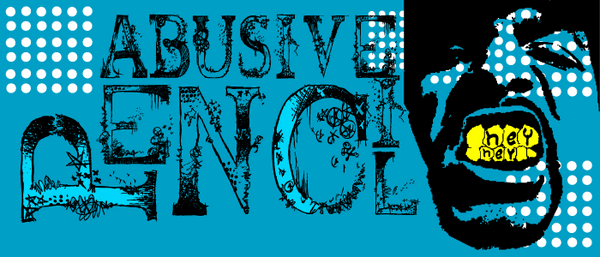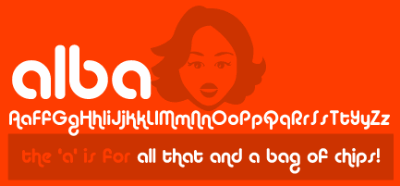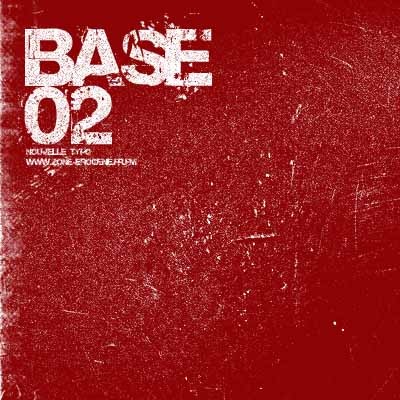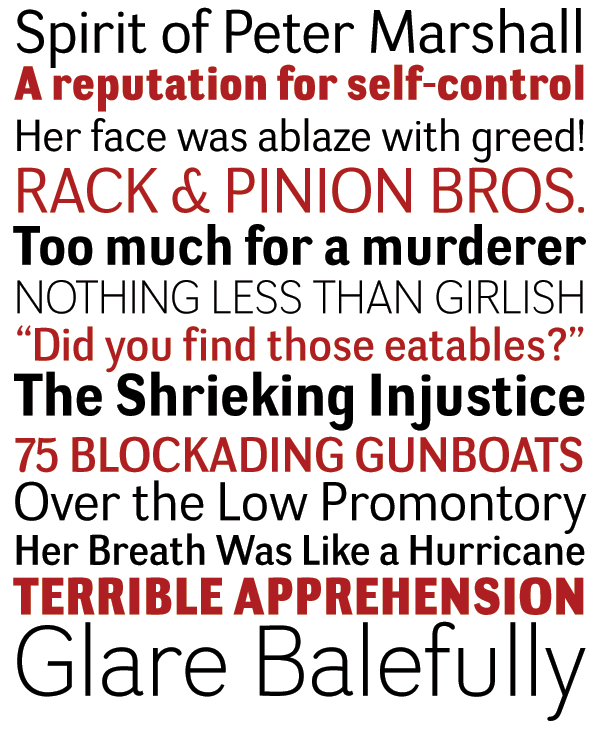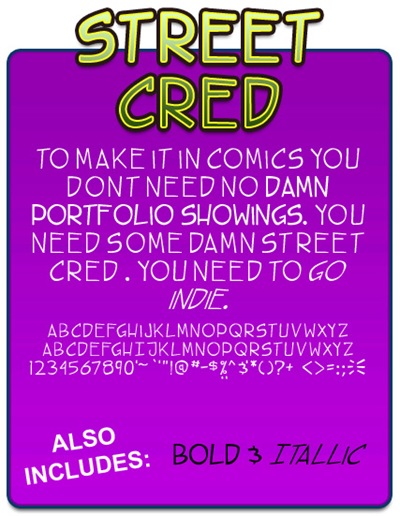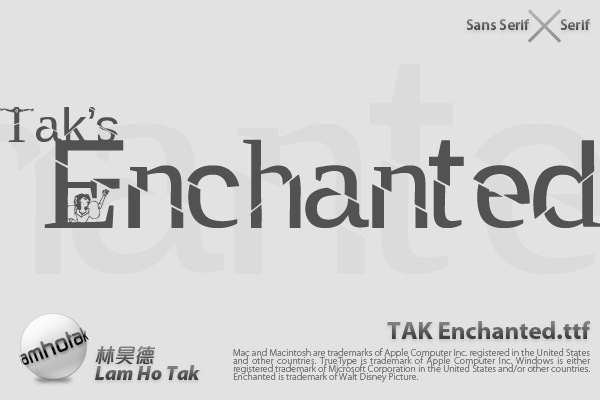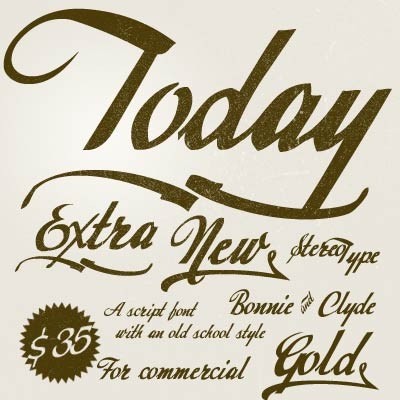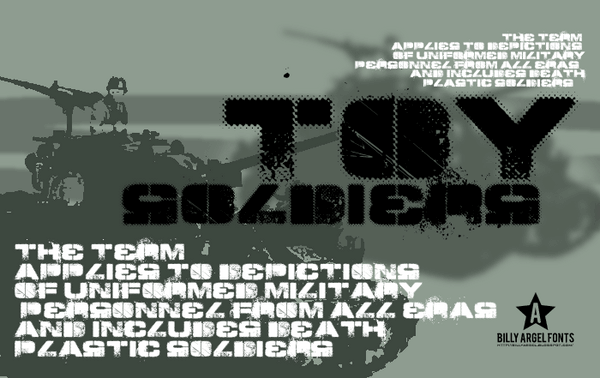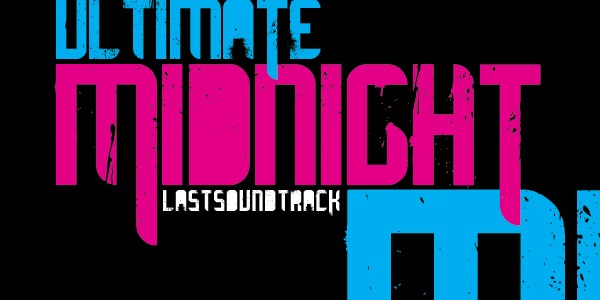
Стильные латинские шрифты
Шрифт под названием “Abusive Pencil”
Стильный шрифт “Acid Label”
Шрифт “Negotiate”
А этот шрифт называется “Tak Enchanted”
Затертый шрифт в стиле гранж “Toy Soldiers”
Урбанистический шрифт “Ultimate Midnight”
Шрифт “Today”
Шрифт “alba”
Крупный шрифт “Base 02”
Шрифт под названием “Street Cred”